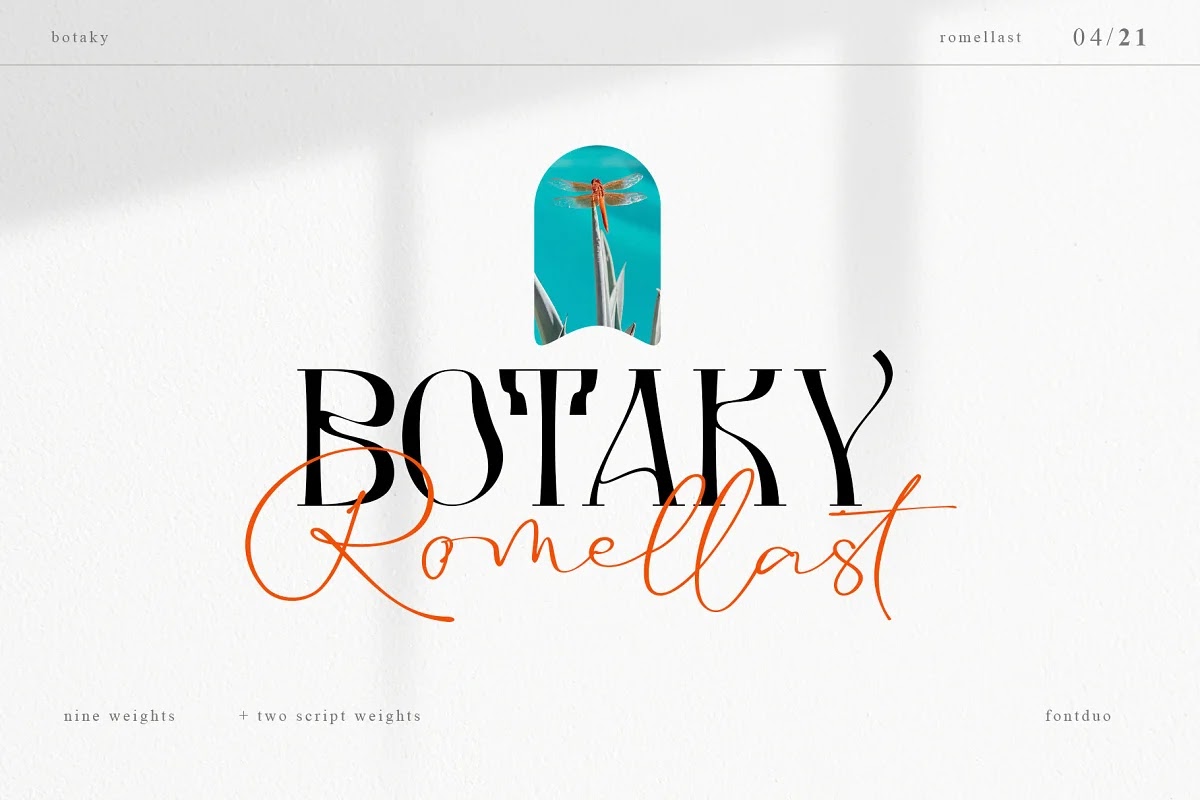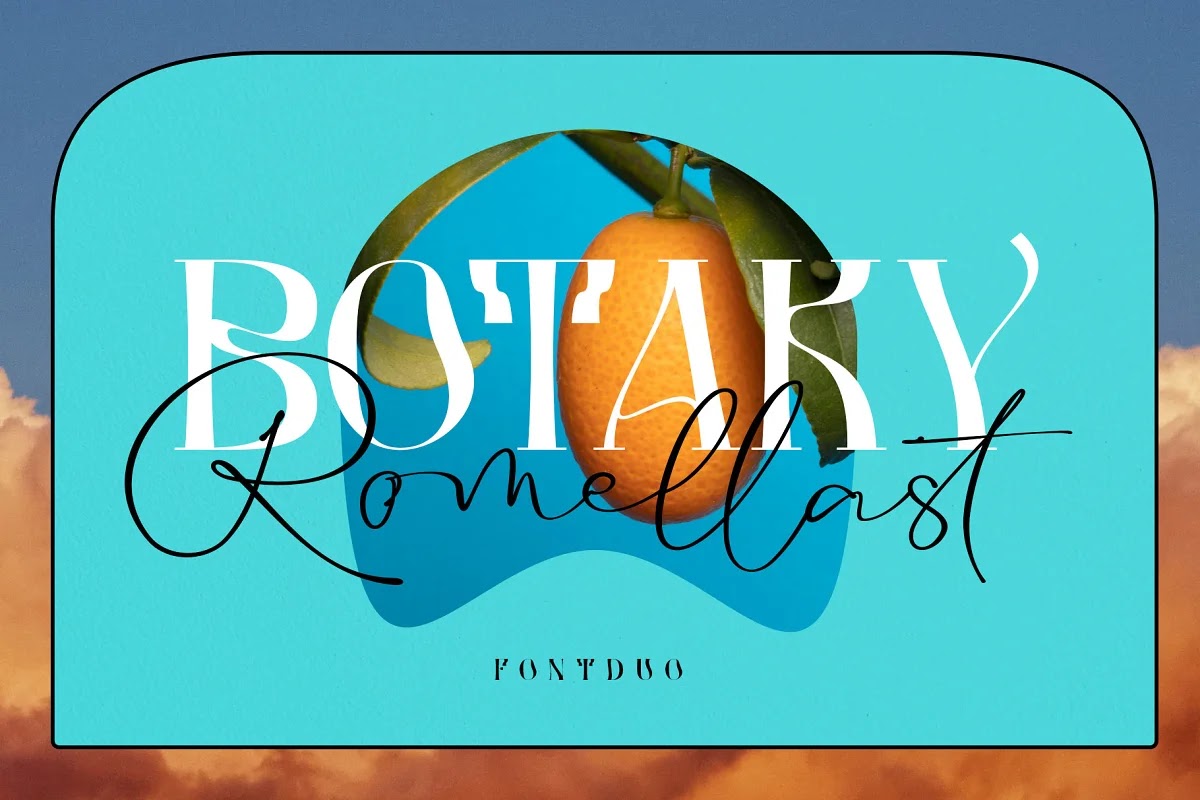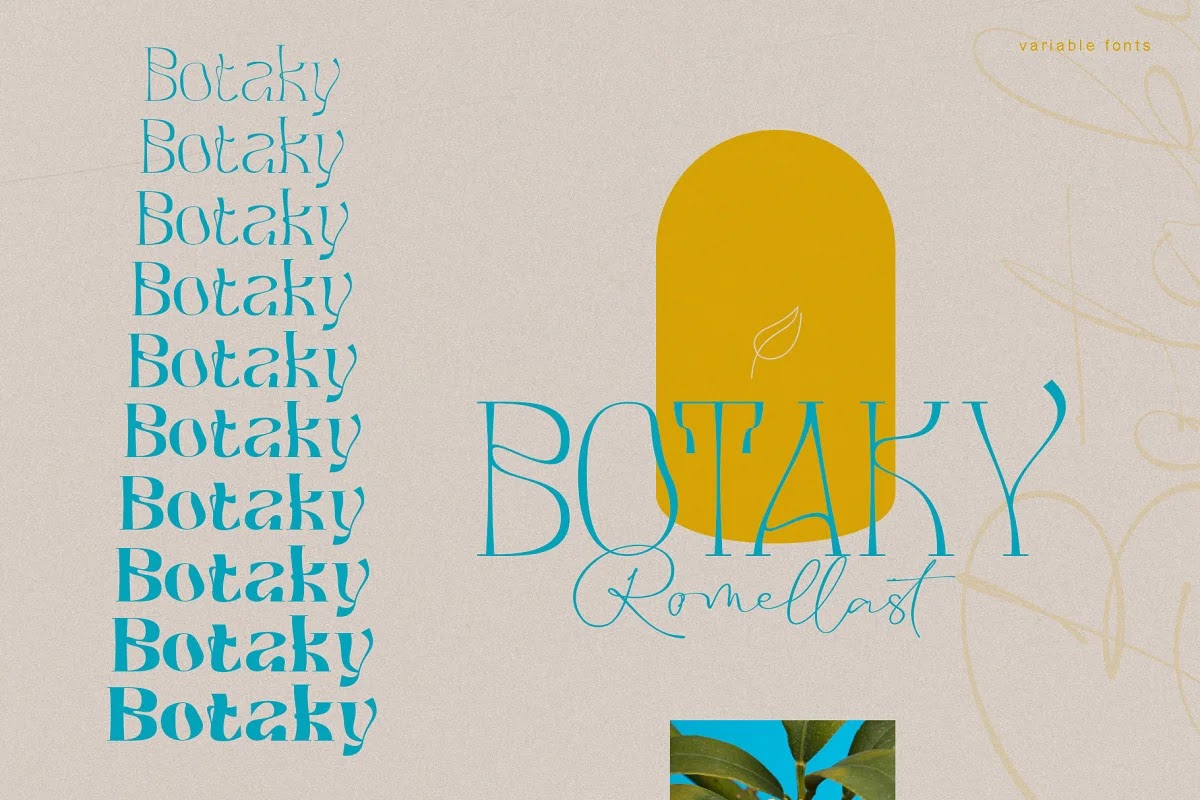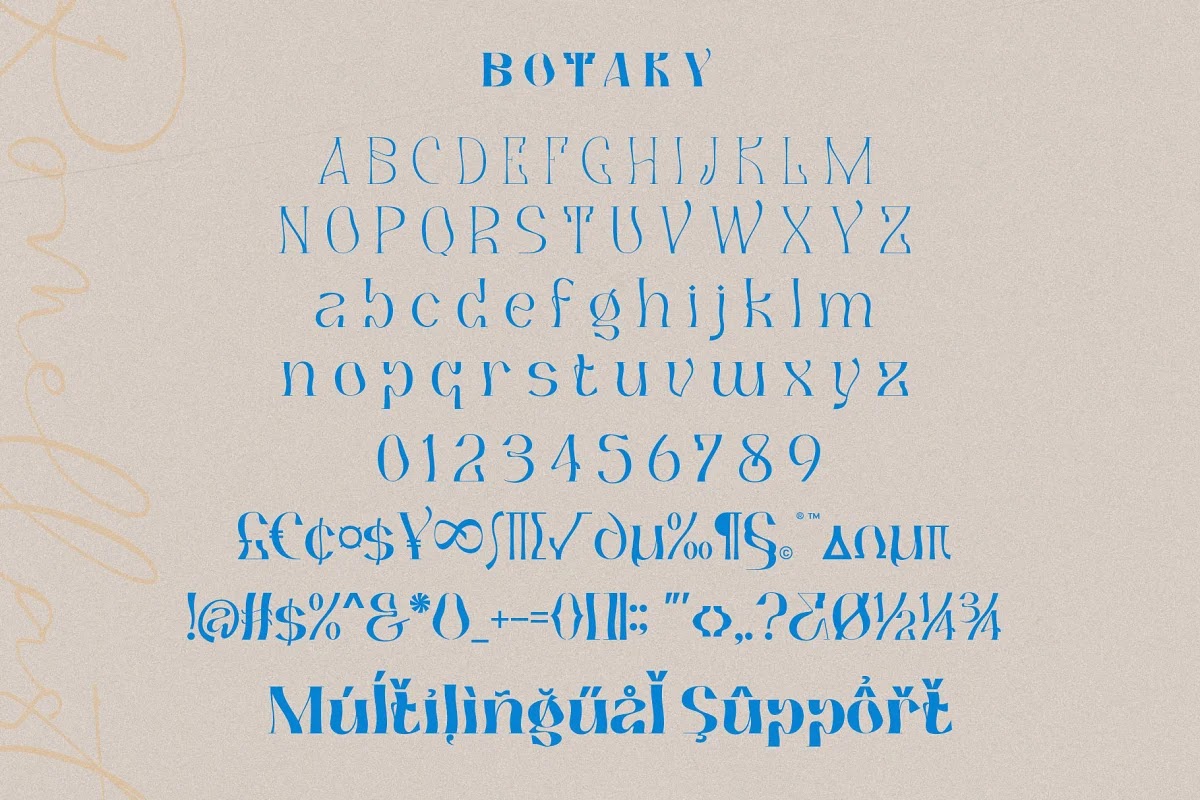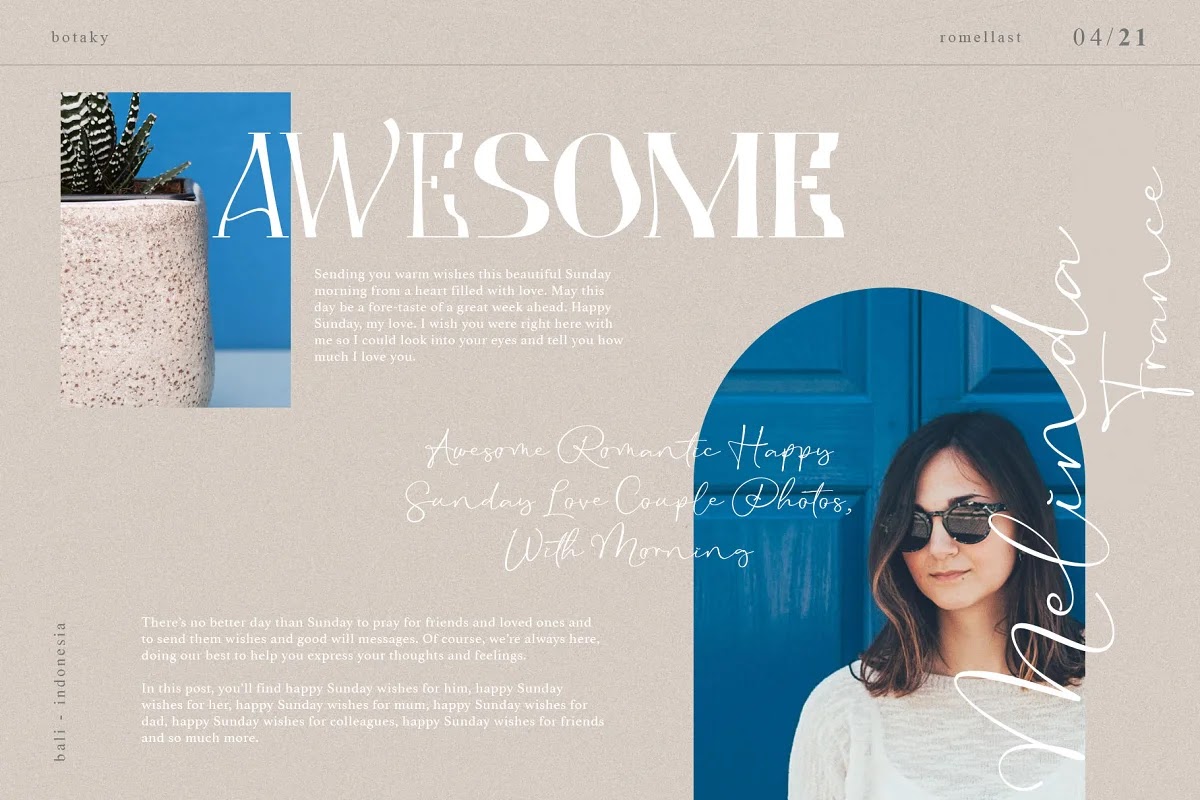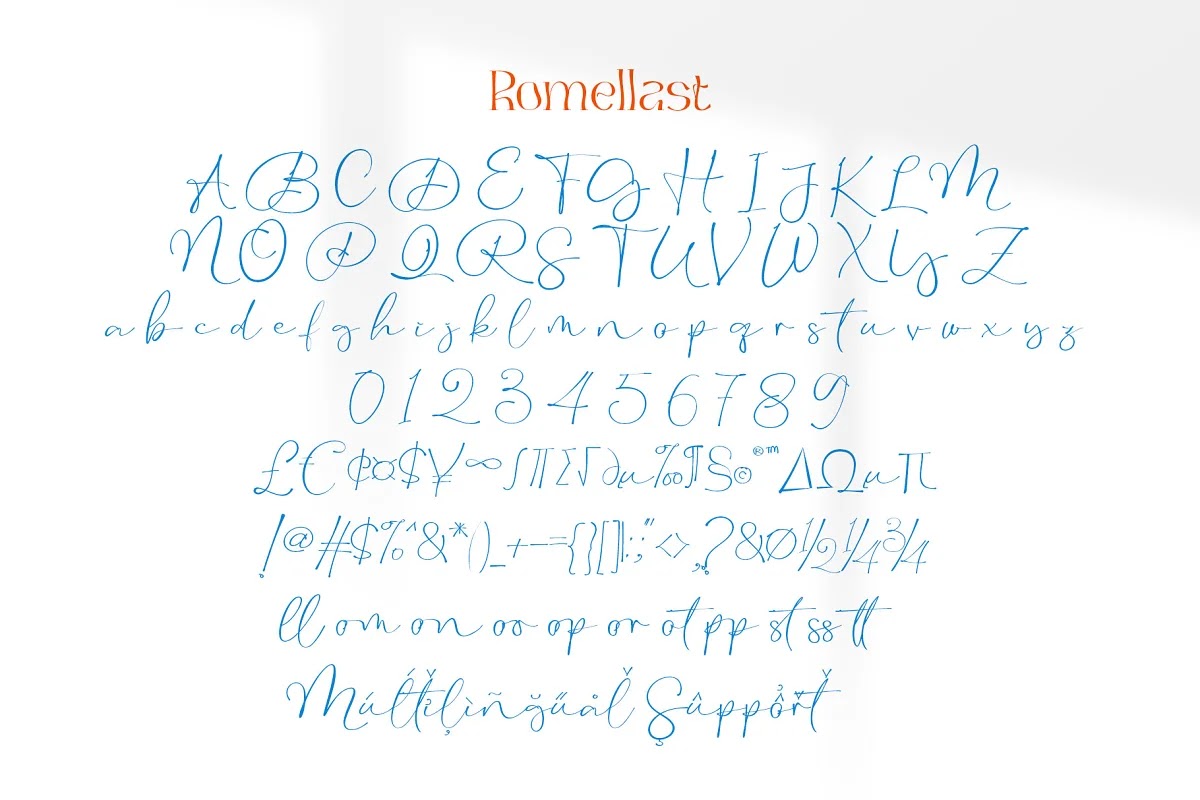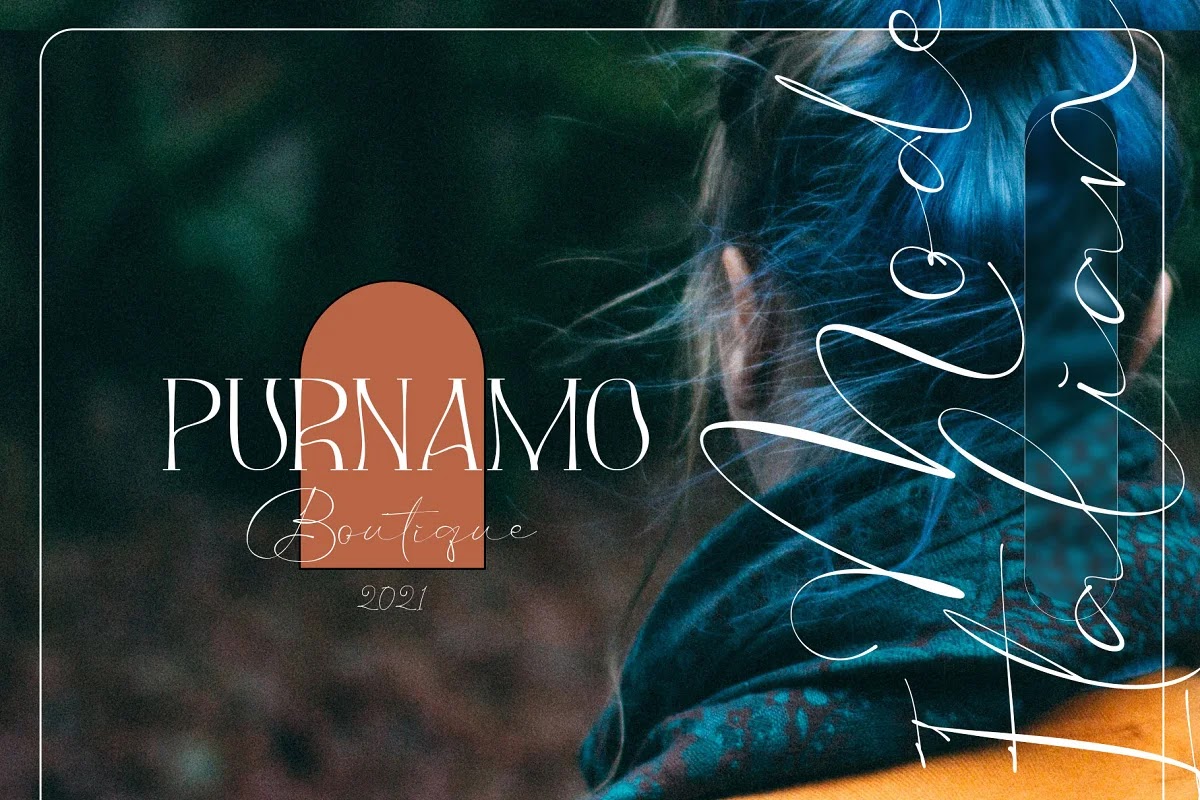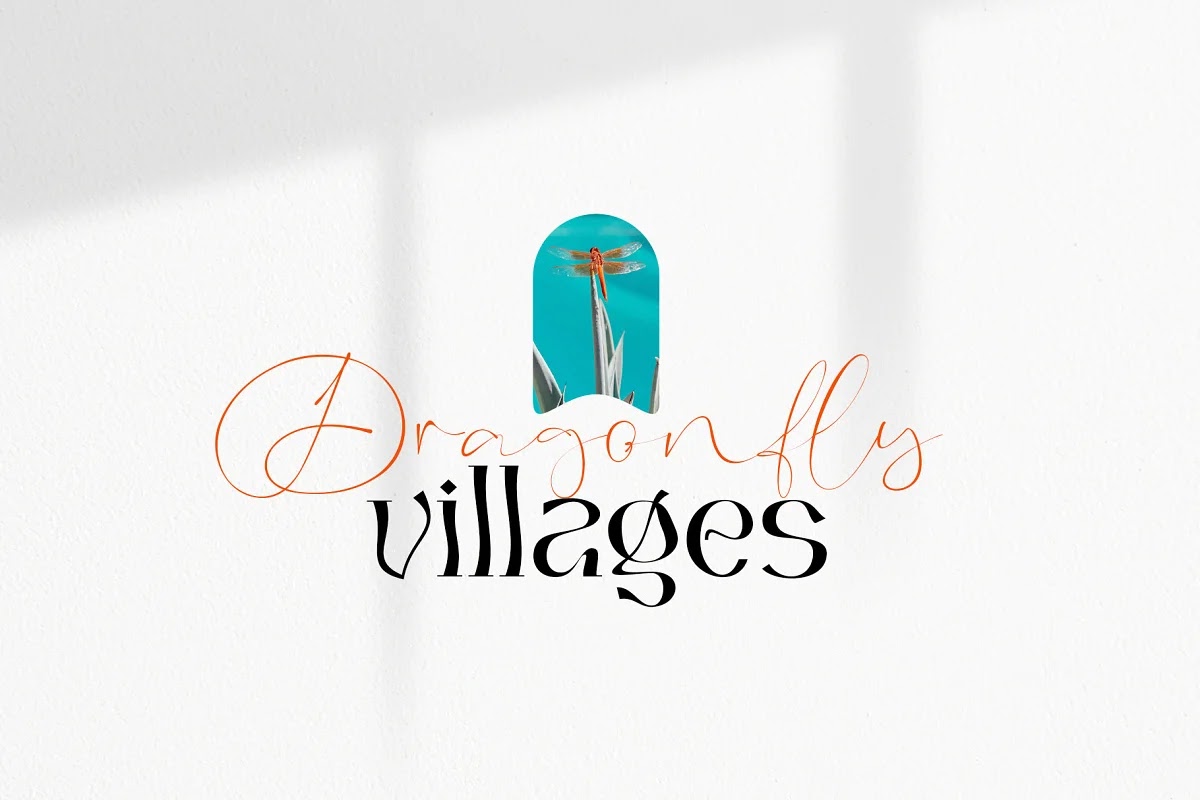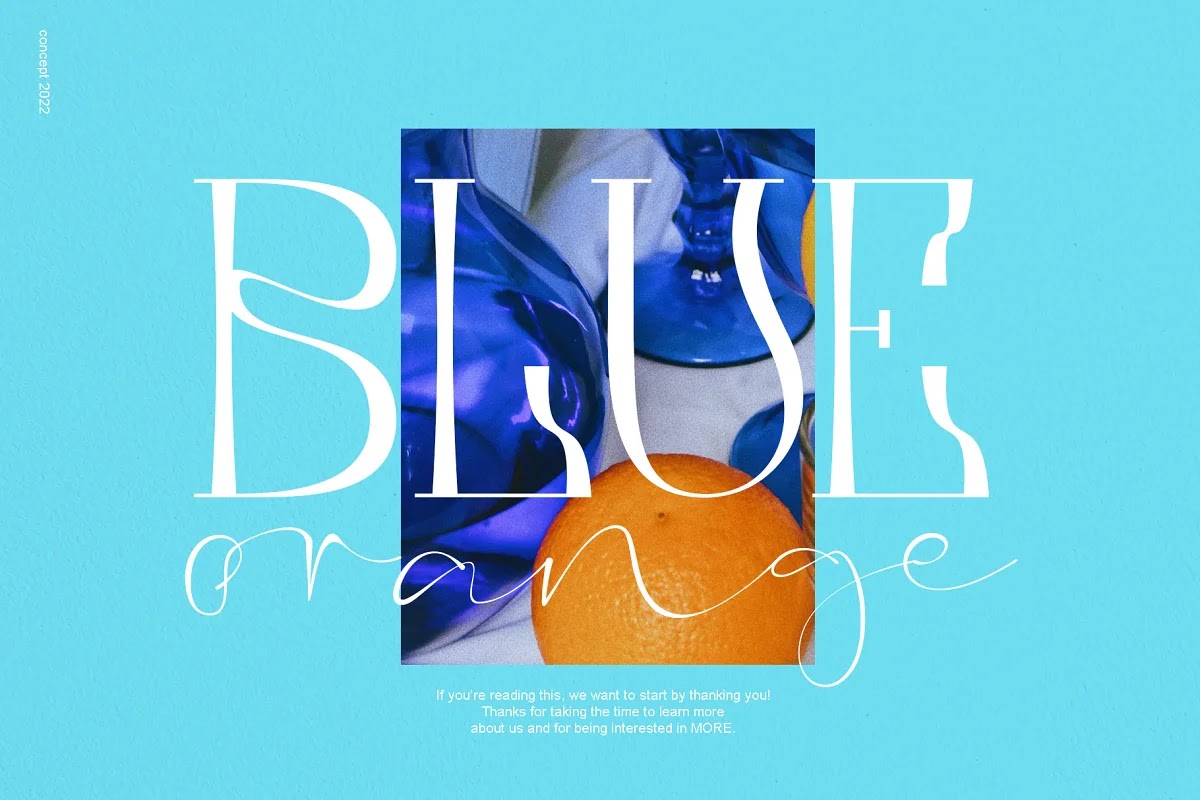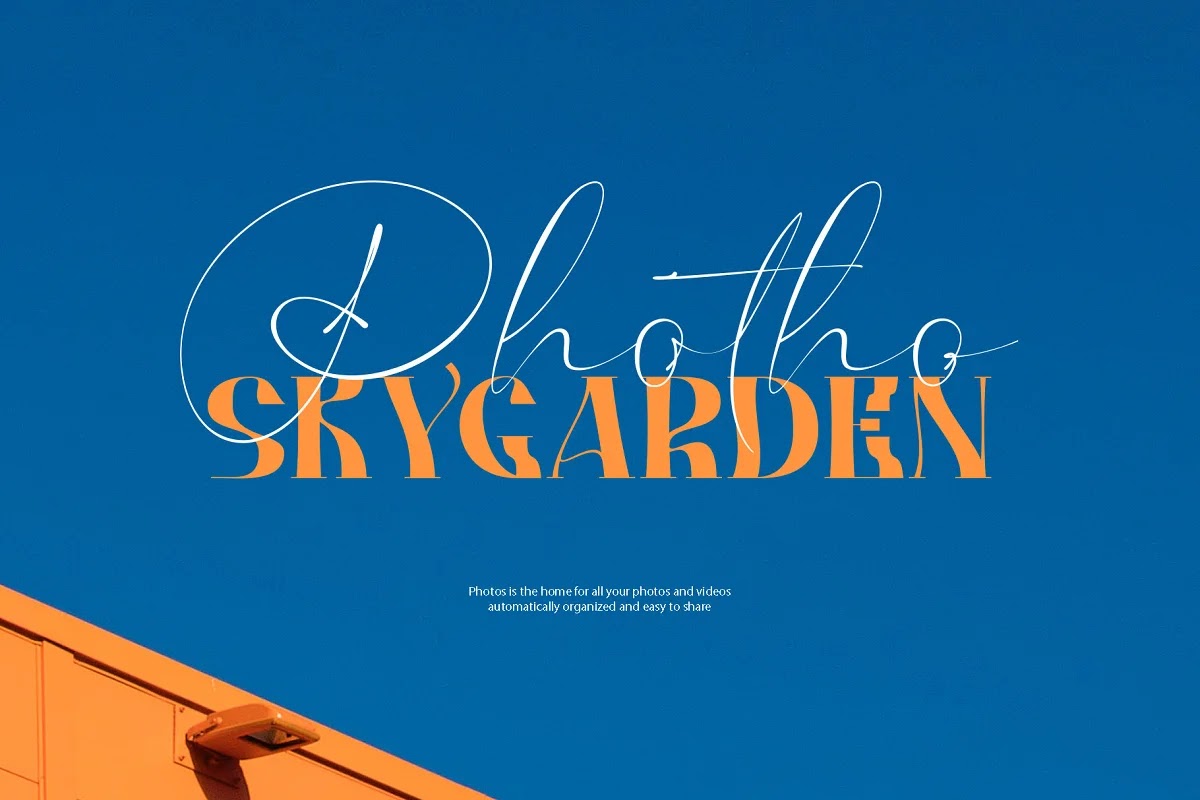
BOTAKY Romellast Font – Font Việt Hóa ấn tượng
Giới thiệu BOTAKY Romellast fontduo – Bộ đôi phông chữ độc đáo và tuyệt vời.
Bộ font BOTAKY bao gồm 12 font, từ phong cách Mỏng đến Đậm. Font chữ với thiết kế độc đáo và chắc chắn sẽ thu hút sự chú ý của đối tượng mục tiêu thiết kế. Ngoài sự độc đáo, font chữ BOTAKY còn có một đặc điểm đơn giản sang trọng làm cho thiết kế trở nên quyến rũ.
Font chữ Romellast là một font chữ dạng viết tay chữ ký có các nét vẽ đẹp. Hình dạng đường kẻ từ Romellast được lấy cảm hứng từ các bút vẽ trên Instagram khi tạo các câu chuyện. Bút vẽ này rất hay và thường được sử dụng bởi những nhà thiết kế. Ngoài ra, Romellast có một đường ghép thay thế trông tự nhiên và không bị cứng. Có 2 kiểu font Romellast, đó là kiểu Thin mỏng hơn và kiểu thông thường dày hơn, vì vậy bạn có một số lựa chọn phù hợp với sở thích của mình.
Kết hợp hai font chữ BOTAKY và Romellast sẽ tạo ra một thiết kế quyến rũ, độc đáo, thanh lịch và hiện đại.
Font chữ này hỗ trợ đa ngôn ngữ và gõ được cả Tiếng Việt luôn nhé các bạn.
BOTAKY Romellast Font